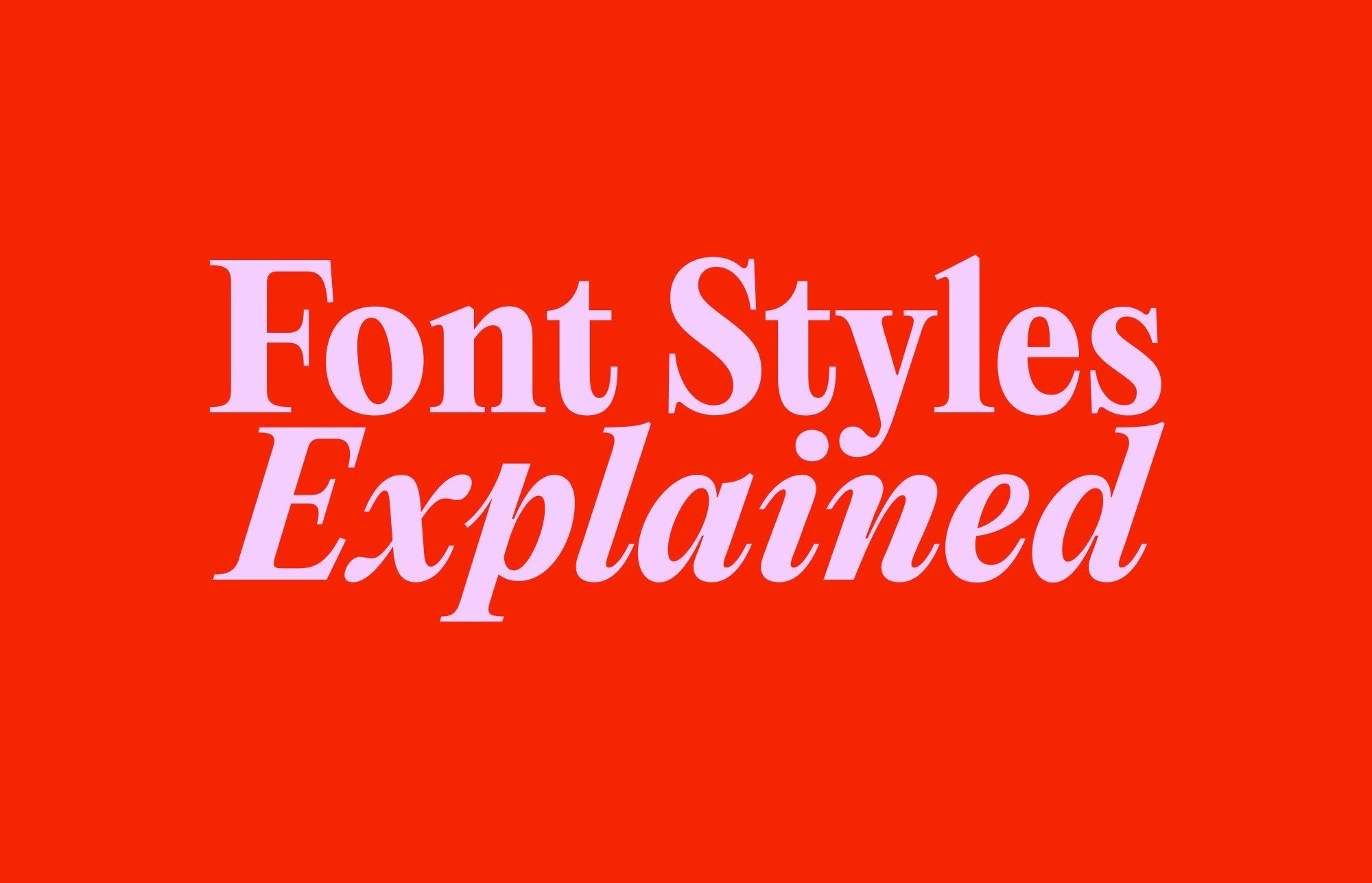
Si vous débutez en graphisme ou créez un site web pour vous-même ou votre entreprise, il est essentiel de connaître quelques notions sur les polices de caractères. Le choix de la police est important. En webdesign ou en branding, c'est la première chose avec laquelle la plupart des gens interagissent. Et la première impression compte aussi. Le choix de la police influence directement l'accessibilité, la perception et la qualité de l'interaction.
C'est pourquoi il est important de connaître les bases, comme les styles de police. Vous serez ainsi mieux informé pour choisir la police qui vous convient le mieux. Après tout, les polices peuvent transmettre beaucoup de choses. Certaines sont plus polyvalentes que d'autres. Certaines sont très percutantes. D'autres sont optimisées pour le web, tandis que beaucoup sont conçues pour l'impression. Quoi qu'il en soit, savoir quel genre de police choisir – et pourquoi – peut faire toute la différence.
Polices Serif
Les polices à empattements se caractérisent par leurs petits traits, ou « pieds », à l'extrémité de leurs traits. Historiquement ancrées dans les inscriptions romaines, les empattements sont associés à la tradition, à l'élégance et à l'autorité, mais cela ne signifie pas pour autant qu'ils soient ennuyeux. Du plus délicat au plus spectaculaire, les empattements apportent une touche de personnalité à la lettre.
Editorial New est une police à empattements qui remplit tous les critères. Classique et contemporain se rencontrent dans cette police à empattements Narrows, aux courbes saisissantes et au contraste saisissant. Avec un léger parfum des années 1990, c'est la police idéale pour la mode, les gros titres, les textes longs ou tout ce qui nécessite une touche d'intensité éditoriale.
PP Hatton
Une police à empattements humaniste et raffinée, inspirée de la signalétique de Hatton Garden à Londres. L'élégance d'antan rencontre la géométrie moderne.
PP Pangaia
Un empattement plus doux, inspiré de la nature, avec des courbes organiques et un rythme terreux.
Polices sans empattement
Les polices sans empattement laissent la place à des lettres épurées et épurées. Elles sont généralement associées à une modernité, une lisibilité et une adaptabilité infinie – le genre incontournable pour les interfaces numériques, sans aucun doute.
Neue Montreal est un classique moderne du genre. Ce grotesque polyvalent allie utilité et style. C'est un outil contemporain qui s'adapte parfaitement aux brandings, aux interfaces utilisateur et même aux sports (oui, il a été utilisé par le Montréal FC, ce qui est plutôt cool).
PP Right Grotesk
Une police sans empattement confiante avec des particularités de personnalité subtiles, parfaite lorsque vous voulez quelque chose de juste... bien.
PP Neue Corp
Neue Corp est une combinaison d'excentricité à l'ancienne - inspirée par les vieux types de bois - et de précision moderne et néo-grotesque.
Polices à espacement fixe
Dans les polices à chasse fixe, chaque caractère occupe le même espace horizontal. Issue de l'impression physique, comme les machines à écrire, elle est aujourd'hui généralement associée au code et aux espaces numériques. De par leur structure, les polices à chasse fixe sont rigides, rythmées et de plus en plus élégantes.
Dotée de fonctions de boutons, de ligatures de codage et d'un vaste jeu de glyphes, Neue Montreal Mono est une police monospace alliant praticité pour les développeurs et esthétique pour les designers. De plus, elle s'associe parfaitement à la coupe standard de Neue Montreal, ce qui en fait une police idéale.
Si vous recherchez une police monospace, vous pourriez également être intéressé par :
PP Lettra Mono
Un mono serif avec un fort contraste vertical et des détails botaniques – idéal pour l'impression, la création de marque ou la conception numérique semi-nostalgique.
PP Model Mono
Épuré, modulaire et inspiré des maquettes en plastique vintage. Technique et soigné, avec hiragana, katakana et glyphes de mesure intégrés.
Les polices d'affichage sont vos atouts. Elles sont fortes, expressives et de préférence utilisées en grand format. Elles sont généralement utilisées comme polices principales dans un design, pour les titres, les affiches, les pochettes d'album, etc. En bref, partout où vous souhaitez attirer l'attention avec une typographie personnelle.
Inspirée des cadrans de s vintage et de la précision horlogère, PP Watch est un parfait exemple de police d'affichage, avec un design large, élégant et rythmique unique. Subtile mais puissante, elle est proposée avec des formes empattement alternées pour une touche d'élégance supplémentaire.
Du serif au sans, du mono au script, connaître vos genres de base (et comment ils se comportent) permet une meilleure conception.